(一) 笔画性变化
抽象的点、横、竖、撇、捺是构成笔画最必需的元素,而笔画又是构成字体的最基本的单位。即:
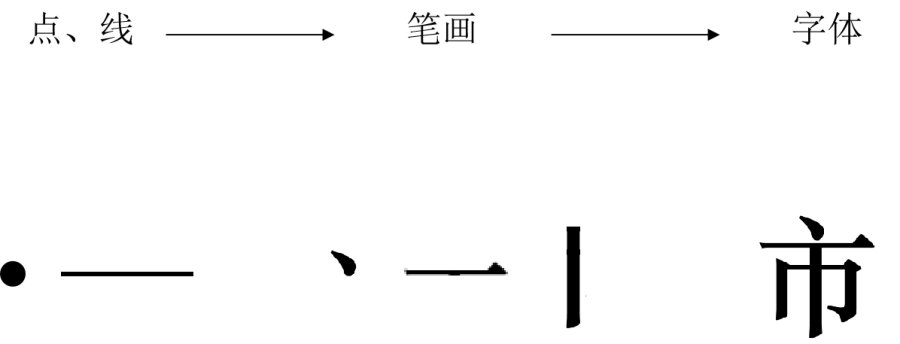
因此,字体设计首先从笔画开始。
1、笔形变异
对笔画的形态做一定的变异,这种变异是在基本字体的基础上对笔画进行改变。
a. 运用统一的形态元素。
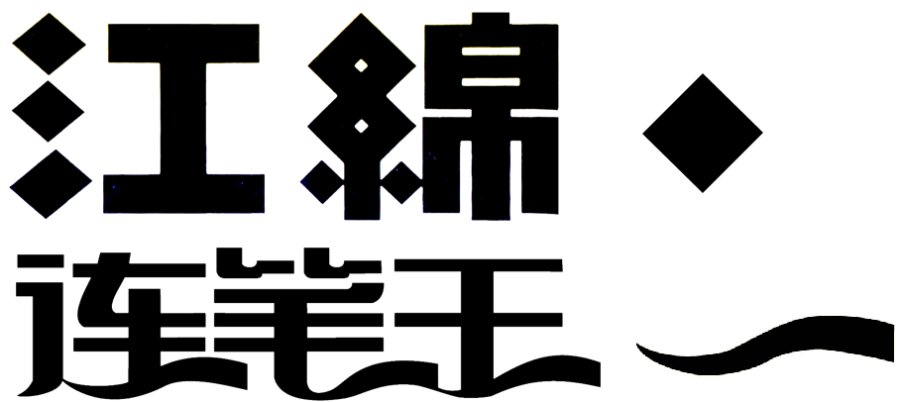
b. 在统一形态元素中加入另类不同的形态元素。
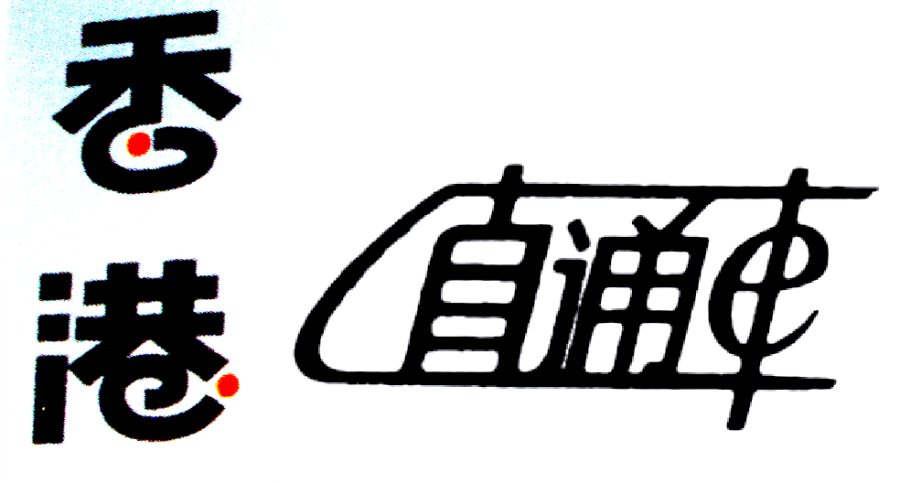
c. 拉长或缩短字体的笔画。
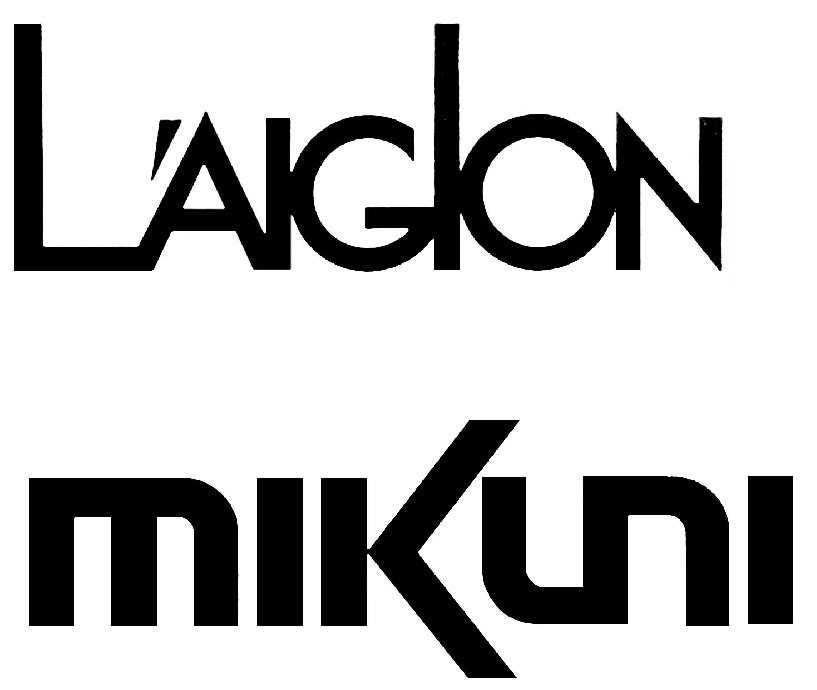
2、笔画共用
既然文字是线条的特殊构成形式,是一种视觉图形,那么,在进行设计时,就可以从纯粹的构成角度,从抽象的线性视点,来理性地看待这些笔画的同异,分析笔画之间相互的内在联系,寻找它们可以共同利用的条件。
借用笔画与笔画之间,中文字与拉丁字之间存在的共性而巧妙地加以组合。